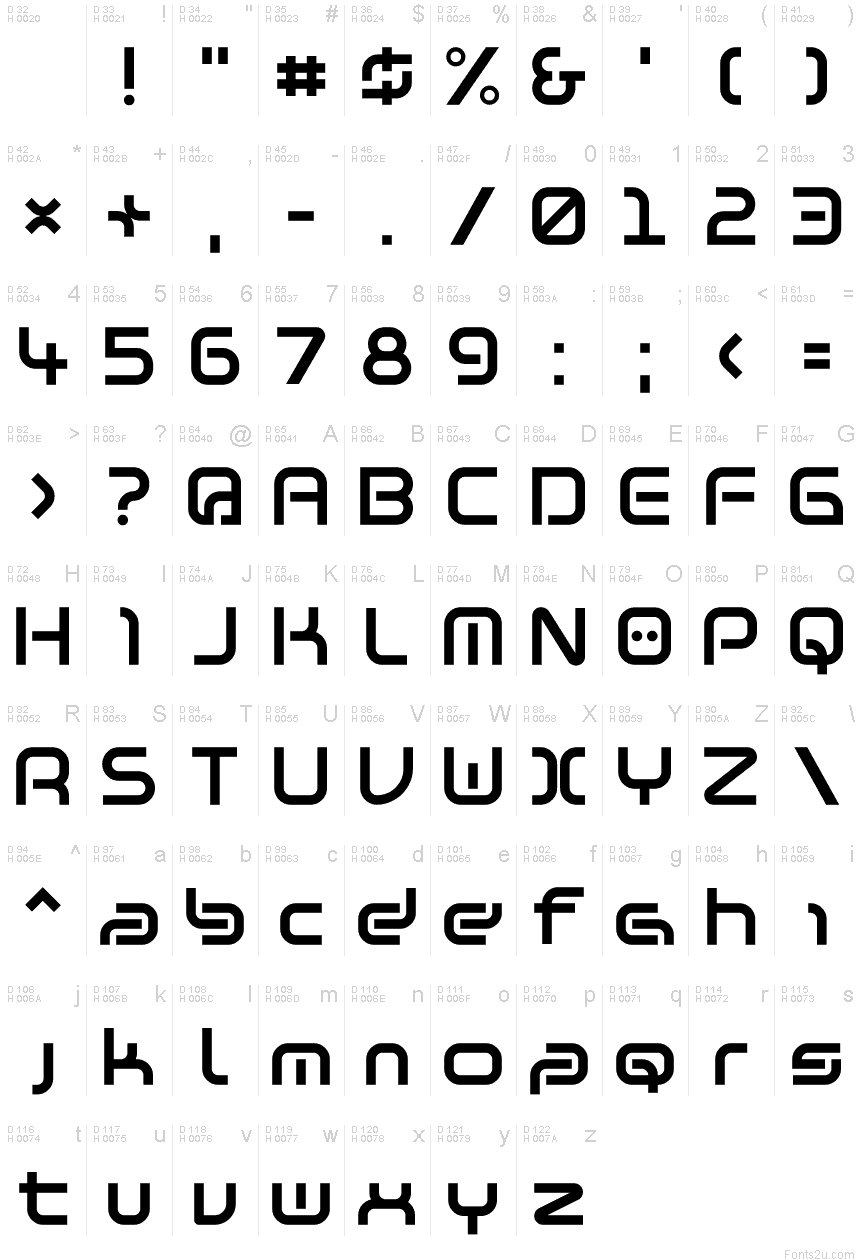
Warzone97 ist eine kostenlose, futuristische Display-Schrift mit minimalistischem Sci-Fi-Charakter. Die Buchstaben bestehen aus wuchtigen, abgerundeten Formen mit scharfen, schlitzartigen Einschnitten – das sorgt für einen technisch-dynamischen Look und eine kompakte Silhouette, die an die Anzeigen aus Videospielen der späten 90er erinnert.
Sie passt perfekt zu Esports-Branding, Arcade-Postern, Tech-Event-Grafiken, Albumcovern und Titeln, bei denen kurze Wörter einen synthetischen Touch brauchen. Da es sich um eine kostenlose Schrift handelt, eignet sie sich auch hervorragend für Logo-Skizzen, Monogramme und Cover-Texte: Die breiten Kurven und markanten Winkel verleihen selbst wenigen Buchstaben einen starken, codierten Look.
Warzone97